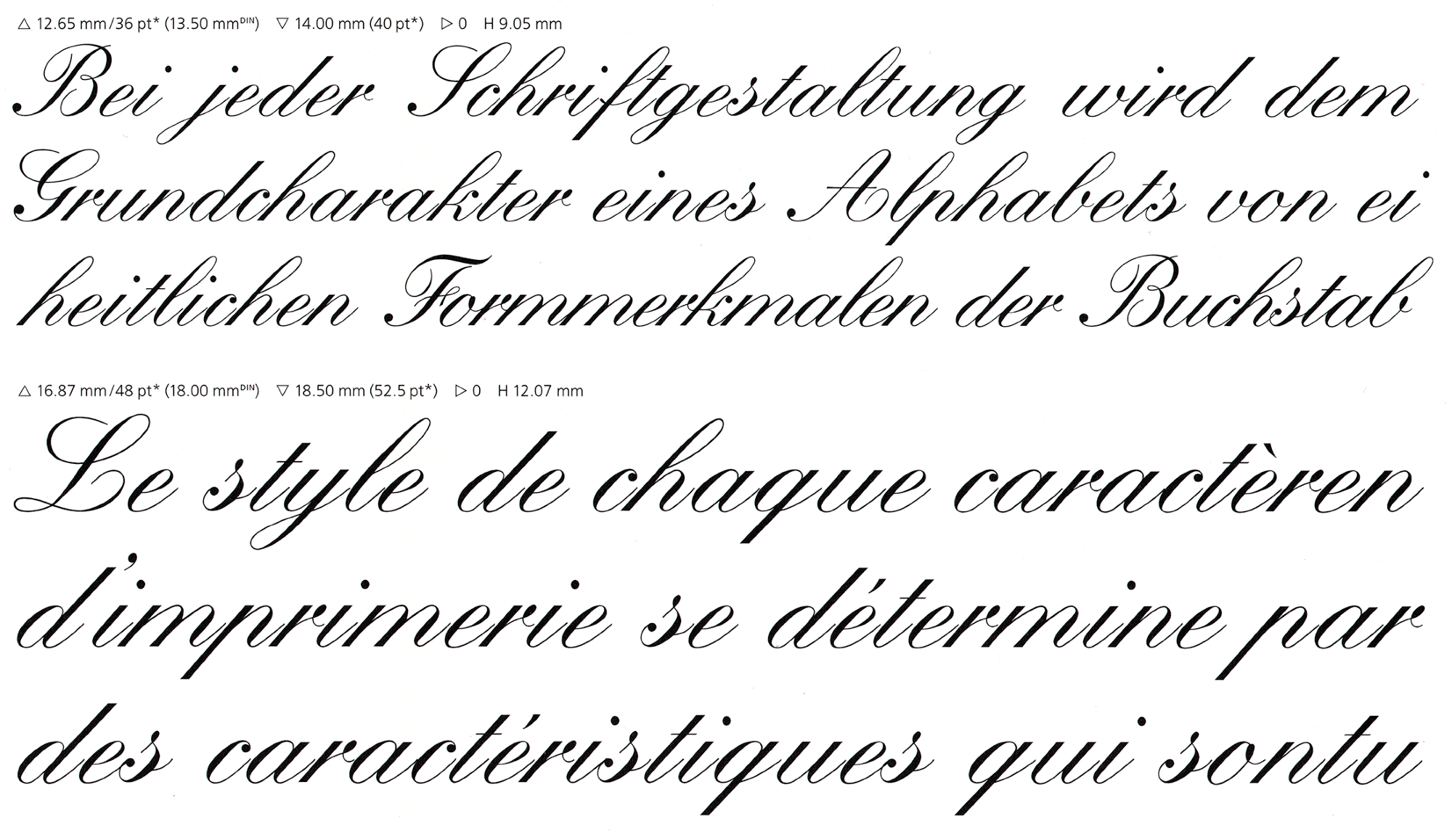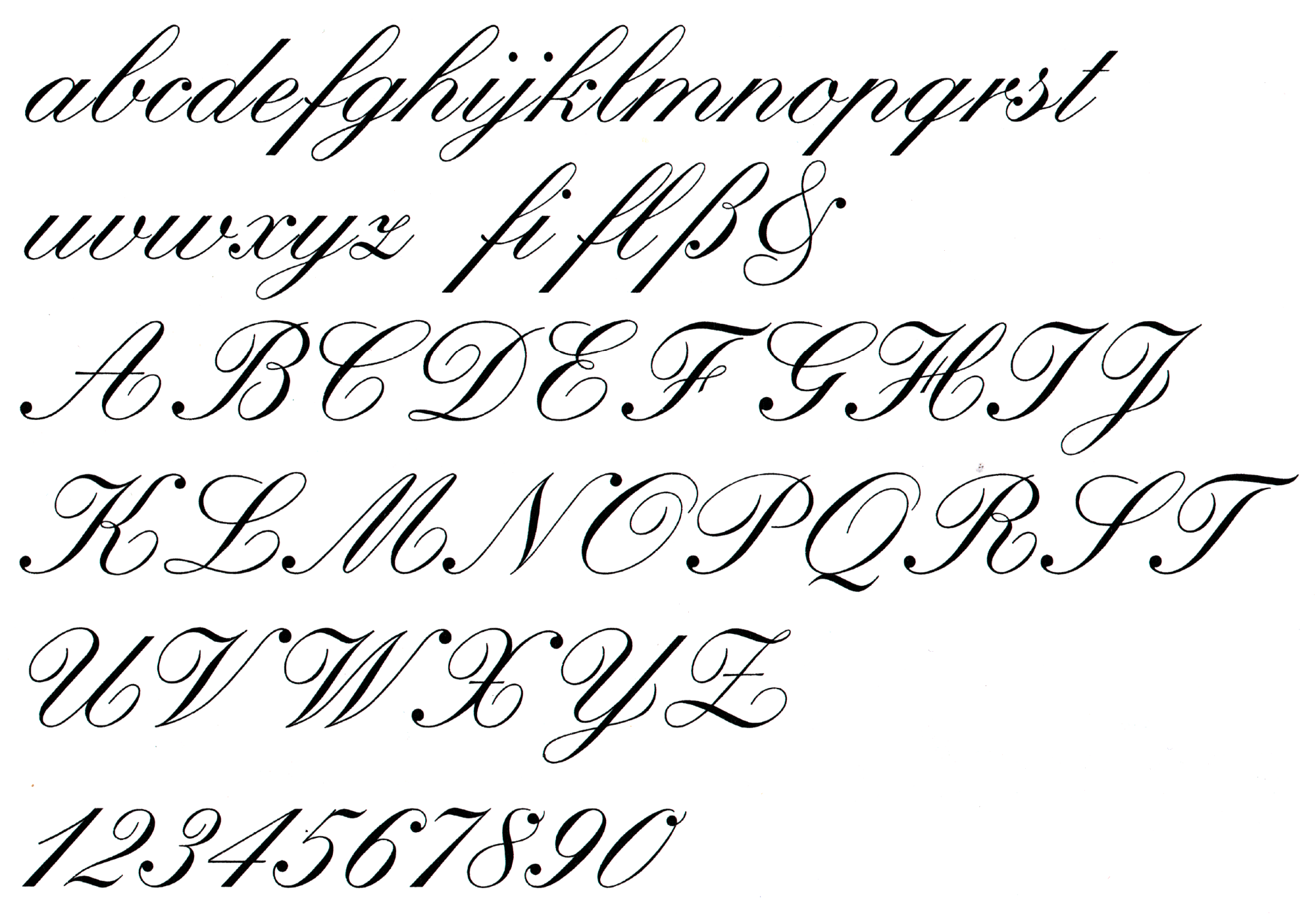
Font-Wiki: Künstler-Schreibschrift
• 1902
• Antiqua Schreibschrift
Die Künstlerschreibschrift (im Englischen Kuenstler Script) entstand zwischen 1902 und 1903 in der Schriftgießerei Stempel. Grundlage bildeten die typischen englischen Kupferstich-Schreibschriften des 18. und 19. Jahrhunderts von Schreibmeistern wie George Bickham und George Shelley.
Als Designer der Künstlerschreibschrift wird oft Hans Bohn genannt. Dieser erweiterte die Familie 1957 jedoch lediglich um einen extrafetten Schnitt.